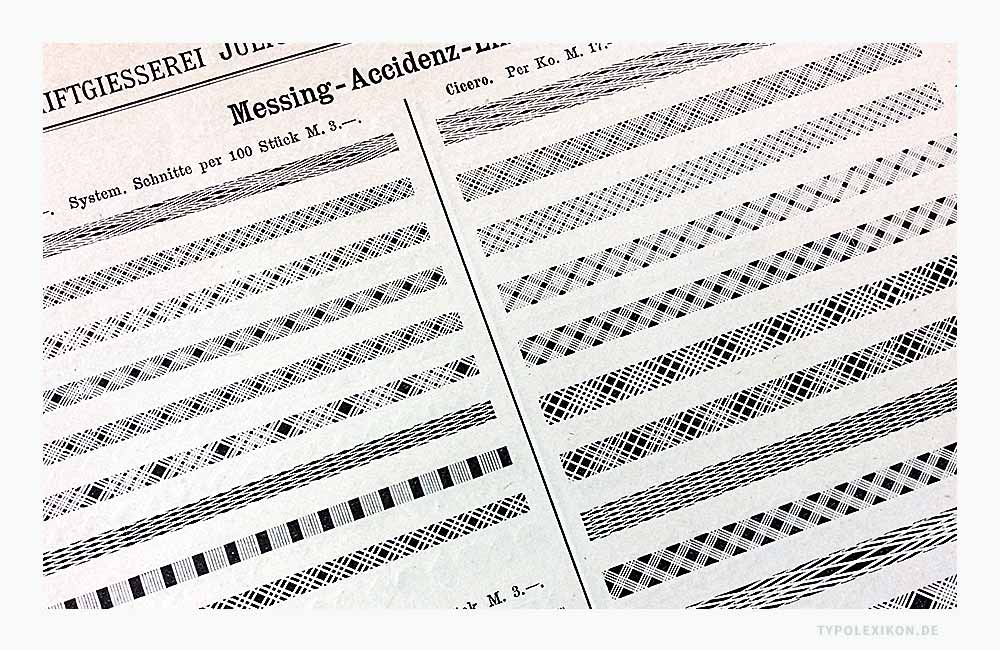
Zierrat
»Zierrat« ist ein typografischer Fachausdruck aus dem gewerbespezifischen Sprachschatz dspr. Schriftsetzer, Schriftgießer und Drucker aus der Periode des materiellen Schriftsatzes mit physischen Drucktypen aus Metall (z.B. aus einer Blei-Zinn-Antimon-Kupfer-Legierung), Holz (z.B. aus Birnenholz) oder Kunststoff (z.B. aus Kunstharz) für dekorative Verzierungen oder Schmuckelemente, die dazu dienen, einen Schriftsatz dekorativ zu gliedern und/oder zu schmücken, beispielsweise mit Schmuckzeichen, Ornamenten oder Linien; typografische Verzierungen; typografische Schmuckelemente. Alternative Schreibweisen in historischen Quellen: »Zierat«, »Typographischer Zierat« und »Acczidenz-Zierat«. 1) 2)
Ursprünglich gehörte der typografische Zierrat zum Buchschmuck 3) und wurde in der Regel bei den Akzidenzschriften aufbewahrt. Dazu zählten beispielsweise Alineas (z.B. Englische Linien), Amoretten (Darstellungen des Liebesgottes Amor), Fleurons (florale Verzierungen), heraldische Symbole (z.B. gemeine Figuren wie Wappentiere oder Fantasiewesen), Rebranken, Vignetten (bildhafte oder abstrakte Schmuckzeichen) 4) oder Voluten (Schneckenformen in der künstlerischen Ornamentik). Auch zählten ehemals dekorative Initialen (z.B. verzierte Anfangsbuchstaben), Schmuckbuchstaben (z.B. Monogramme), Lunetten bzw. Lünetten (halbkreisförmige oder kreissegmentförmig gerahmte Motivfelder), Bordüren (verzierte Einfassungen) und Rahmen dazu. 5)
»Verzierte Schluss-Linien« für den Bleisatz. Abbildung: Schriftmusterbuch »Schrift-Proben« der Schriftgießerei Julius Klinkhardt, Leipzig und Wien, Handausgabe, ca. 1885. Foto: www.typolexikon.de
»Verzierte Schluss-Linien« für den Bleisatz. Abbildung: Schriftmusterbuch »Schrift-Proben« der Schriftgießerei Julius Klinkhardt, Leipzig und Wien, Handausgabe, ca. 1885.
Alineas sind Schmuckzeichen, Zierstücke, Vignetten oder Schlusslinien zur Text- oder Raumgliederung. Beispiel gesetzt aus der Linotype Decoration P1 von Linotype. Infografik: www.typolexikon.de
Alineas sind Schmuckzeichen, Zierstücke, Vignetten oder Schlusslinien zur Text- oder Raumgliederung. Beispiel gesetzt aus der Linotype Decoration P1 von Linotype.
Das Aldusblatt (Hedera-Zeichen) ist ein blumenartiges Alinea (Zierornament), das im deutschsprachigen Raum nach dem venezianischen Typografen Aldus Manutius (1449–1515) benannt wurde, der es gerne in seinen Aldinen verwendete. Vom Aldusblatt gibt es heute unzählige Varianten. Beispiel: Drei Aldusblätter aus der Schrift »Minion Pro« (Display) von Robert Slimbach.
Messing-Accidenz-Linien für den Bleisatz. Abbildung: Schriftmusterbuch »Schrift-Proben« der Schriftgießerei Julius Klinkhardt, Leipzig und Wien, Handausgabe, ca. 1885.
Eine generelle, übergreifende Klassifikation von Zierrat existierte nicht. Jede Epoche, jede Schriftgießerei und jede Offizin hatte ihr eigenes Klassifikationsmodell, was vermutlich abhängig von der Größe der Buch- und Zeitungsdruckerei bzw. dem Spezialisierungsgrad der jeweiligen Akzidenzsetzerei war.
Zierrat gab es in allen gängigen Kegelgrößen, metrischen Größen, nach Gewicht oder am laufenden Meter. Der ein oder andere Zierrat erhielt – wie auch bei physischen Drucktypen üblich – Mittelnamen. Beispielsweise wurde die Größe eines Schmuckzeichens in ca. 4,5 mm bis 5 mm auch als »Cicero« bezeichnet.
Die grafische Gestaltung von Zierrat passt sich bis heute modischen Strömungen an. Zu den produktivsten Epochen im materiellen Schriftsatz zählen sicherlich der Jugendstil und Historismus bzw. die Gründerzeit.
Heute ist die Vielfalt von Zierrat unüberschaubar. In der aktuellen Schriftklassifikation wird er bei den Bildzeichen (Symbol oder Icon Fonts) oder ggf. bei den Zierschriften eingruppiert. Gegenwärtig zählen zu den prominenten Beispielen vermutlich die »ITC Zapf Dingbats« von Hermann Zapf (1918–2015) oder der Symbol-Font »Wingdings« von Microsoft ®.
1 Die Herkunft des Wortes liegt im Mittelhochdeutschen, zusammengesetzt aus »Zier« (Dekoration) und »Rat« (Waren, Dinge).
2 Literaturempfehlung: Walther, Karl Klaus: Lexikon der Buchkunst und Bibliophilie, Verlag: Leipzig: VEB Bibliographisches Institut, 1987, ISBN 10: 3323000935 und ISBN 13: 9783323000933.
3 Literaturempfehlung: Gerlach, Martin (Hrsg.): Das Alte Buch und seine Ausstattung vom XV. bis zum XIX. Jahrhundert. Buchdruck, Buchschmuck und Einbände, Verlag Gerlach & Wieldling Wien und Leipzig, 1915/18. Online verfügbar im Internet Archive unter https://archive.org/details/dasaltebuchundse00gerl (11.4.2024).
4 Anmerkungen: In einigen typografischen Lehrbüchern wird darauf hingewiesen, dass Vignetten nicht zum Zierrat zählten (Beispiel: Luidl, Philipp: Typografie, Herkunft, Aufbau, Anwendung. Schlütersche Verlagsanstalt und Druckerei, Hannover, 1984, ISBN 3–87706-212–1, Seite 51).